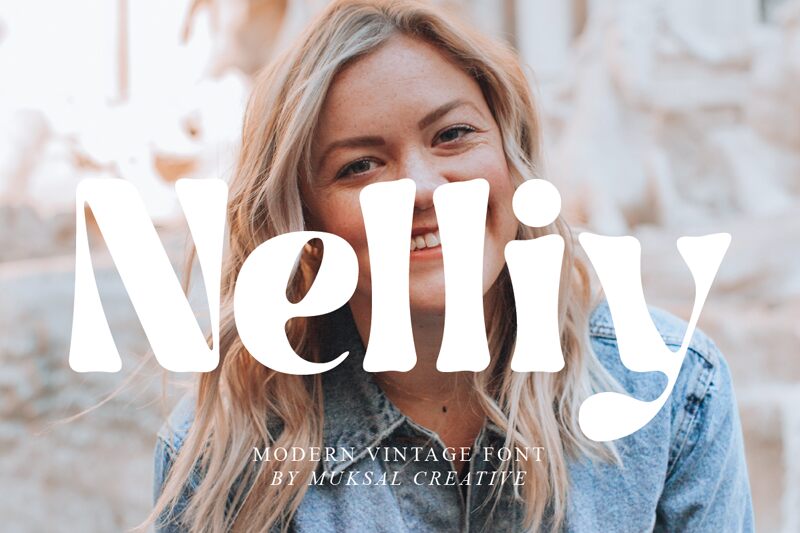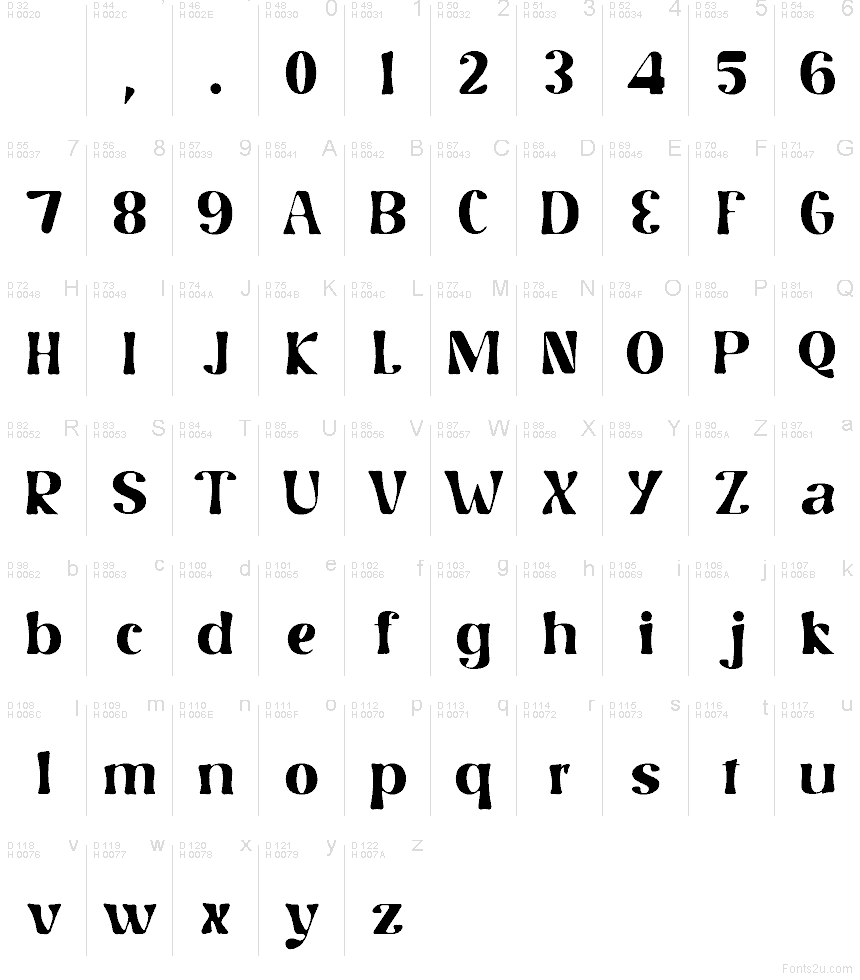
Nelliy Regular
Nelliy, navrhnutý štúdiom Benya Muksal Craeative v roku 2021, je bezplatný retro font typu display, ktorý definujú výrazné vertikály, jemné zúženia a ľahko hravá silueta. Písmená pôsobia na pohľad mäkko a zámerne trochu nevycentrované, čo im dodáva uvoľnený, nostalgický nádych sedemdesiatych rokov, čím sa odlišuje od neutrálnych dizajnov.
Vďaka svojim zaobleným tvarom a uvoľnenému rytmu je Nelliy skvelou voľbou pre branding kaviarní, obaly albumov, butikové balenia, plagáty na podujatia či hlavičky na sociálnych sieťach. Krátke nápisy obzvlášť ťažia z jeho širokých, výrazných foriem, ktoré dokážu vizuálne ukotviť celú sadzbu bez potreby ďalších dekorácií alebo zložitého stylingu.